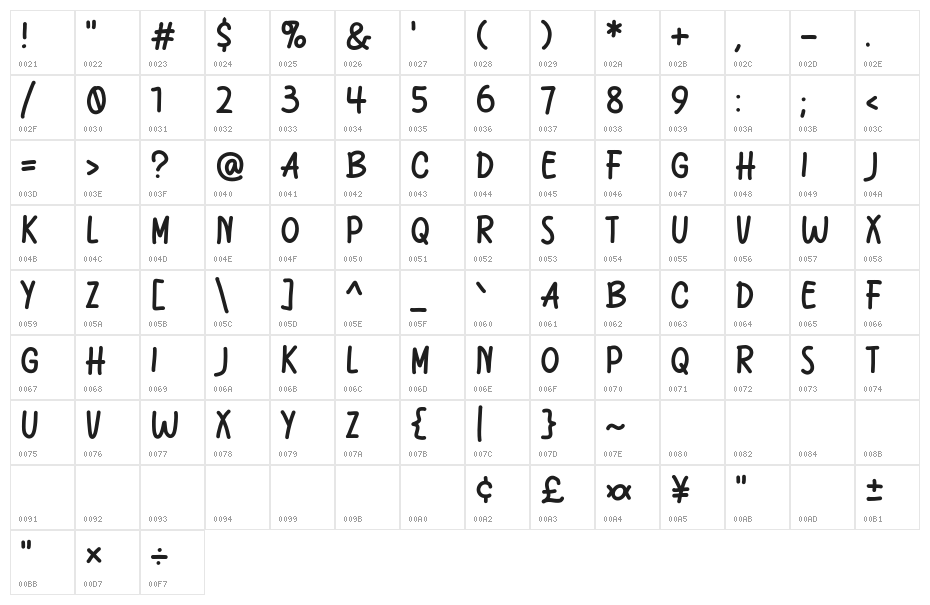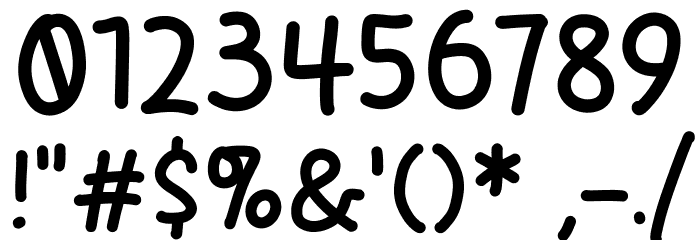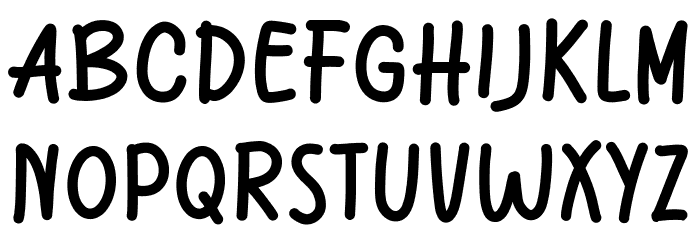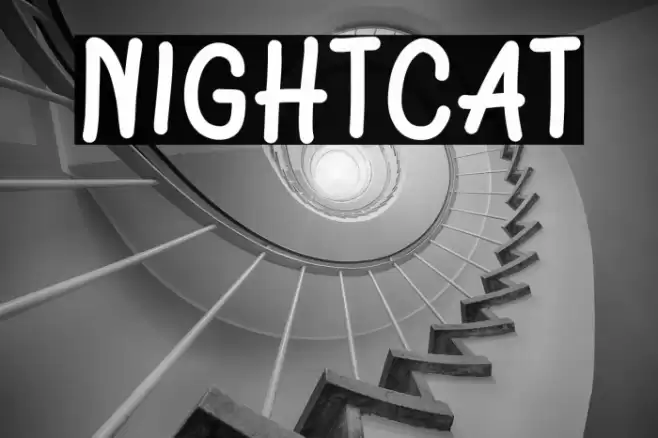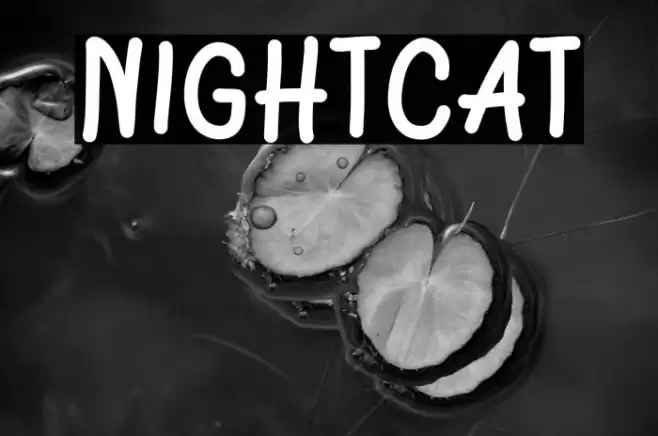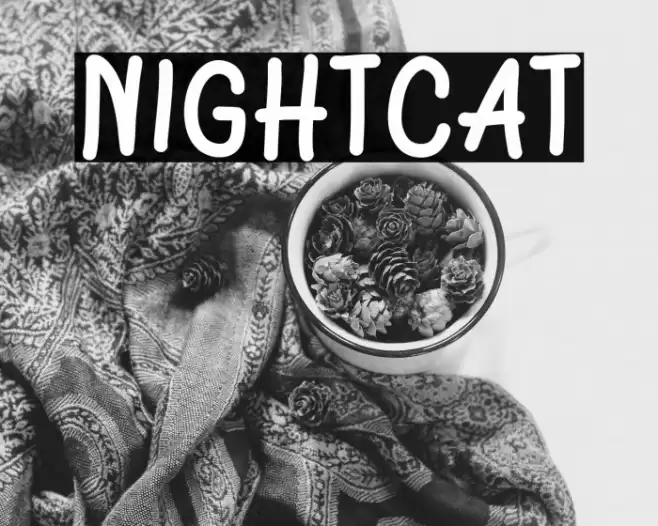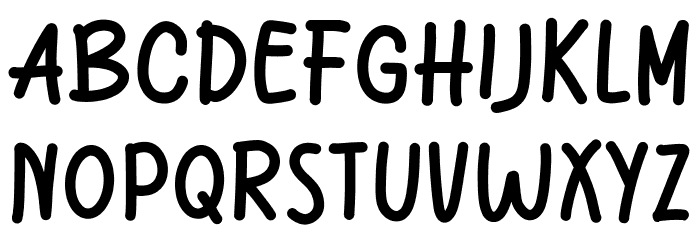
Nightcat Font
| النمط العام | Playful |
| حالة الاستخدام | Headlines, Logos, Informal Text |
| مشاريع مقترحة | Ideal for children's books, playful branding, casual invitations, and social media graphics. |